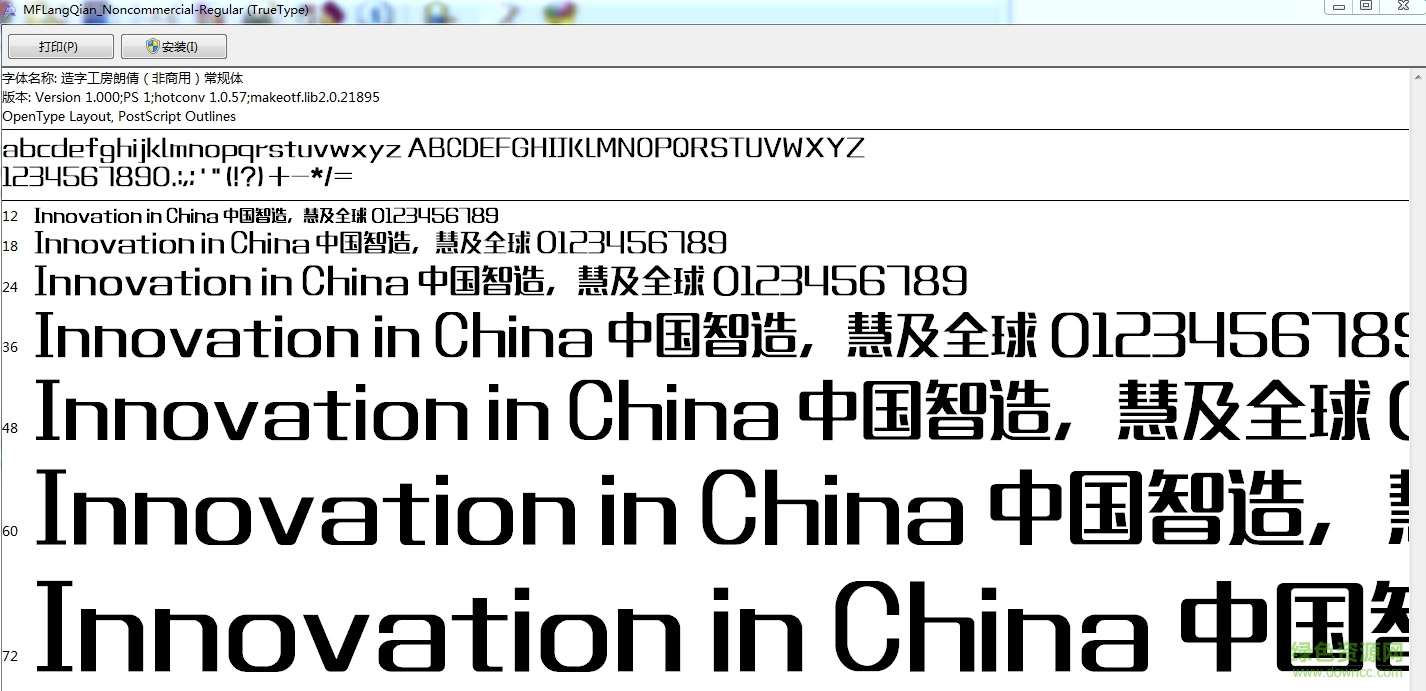
造字工房朗倩(非商用)字體是一款造字工房類浪漫清新風(fēng)格字體軟件,朗倩體給人非常輕松簡約的感覺,在廣告標(biāo)題設(shè)計(jì)方面有較深的應(yīng)用,也深受廣大書法家的喜愛,還有更多好看字體盡情期待,歡迎到綠色資源網(wǎng)下載體驗(yàn)!
造字工房朗倩體是一款應(yīng)用于藝術(shù)設(shè)計(jì)方面的字體,字形美觀大方,其筆畫的設(shè)計(jì)在直線與曲線有著良好的平衡取舍關(guān)系,適用于標(biāo)題、副標(biāo)題等視覺環(huán)境。